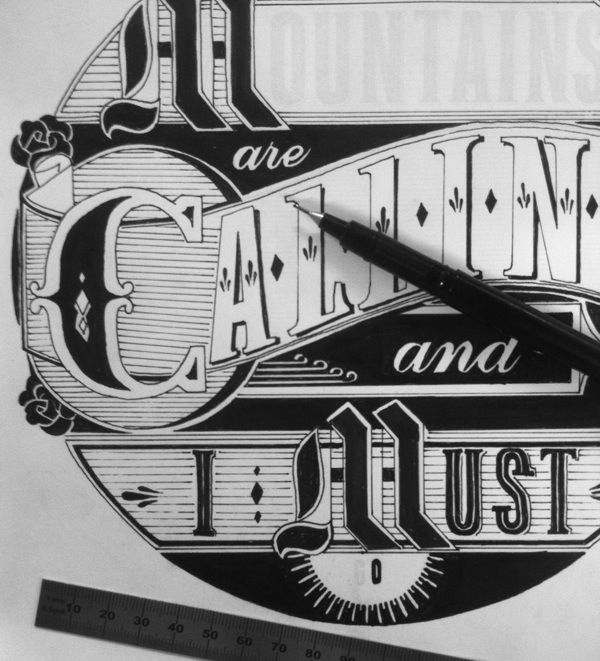
La habilidad de Ben Johnston como tipógrafo y su experiencia en el diseño industrial, junto al talento de Mark Simmons en la transformación en objetos 3D de imágenes impresas, han dado origen a este proyecto: la creación de esculturas de PLA (bioplástico) en las que las letras de Johnston adquieren profundidad y peso.
Tipografía 3D, Ben Johnston y Mark Simmons, 2014.
Ben Johnston, autodidacta canadiense de 26 años, se dedica a la ilustración de tipografías. Con su técnica de rotting negro sobre fondo blanco hace que las letras den forma a imágenes: dibujos, murales, sellos o diseños animados. Su experiencia en el diseño industrial ha permitido a este artista romper los límites de la bidimensionalidad y dar vida a sus tipografías, ahora convertidas en esculturas 3D. Ben Jonhston trabaja, desde su estudio en Toronto, como freelancer.
Tipografía 3D, Ben Johnston y Mark Simmons, 2014.
Diseño en 3D es un proyecto ideado por Ben Jonhston que, esta vez, decide colaborar con Mark Simmons en la realización de la obra. La motivación principal de ambos es la de crear una pieza única. El talento individual de cada autor, de Jonhston como ilustrador y de Simmons como proyectista, ha dado vida a estas esculturas que, como afirman, “ninguno de los dos habrían podido construir de manera independiente”.
Tipografía 3D, Ben Johnston y Mark Simmons, 2014.
Las esculturas en 3D combinan, así, dos disciplinas siamesas: el diseño gráfico y el diseño del producto. El proceso comienza con Jonhston que ilustra a mano y en línea negra una frase arrítmica, siempre asimétrica, decorada con relieves y sombras, para que después sea refinada ajustándola a un formato digital de vectores.
Tipografía 3D, Ben Johnston y Mark Simmons, 2014.
Para dar la forma 3D, los autores utilizan el programa CAD (Computer – aided designed) que asiste en la modificación, análisis y optimización de la imagen, perfeccionándola y mejorando su calidad. En el ordenador, el boceto es representado y animado hasta que finalmente, con una impresora 3D, Simmons hace del diseño, un objeto físico.
Tipografía 3D, Ben Johnston y Mark Simmons, 2014.
Cada escultura se limita, en su composición, a tres piezas, de manera que el volumen de material impreso es el mínimo. El material utilizado, denominado PLA, se ajusta, además, a un enfoque ecológico, ya que el bioplástico es un tipo de plástico derivado de productos vegetales, como el aceite de soja, el maíz o la fécula de patata que, a diferencia de los plásticos convencionales, no deriva del petróleo.
Tipografía 3D, Ben Johnston y Mark Simmons, 2014.
Las impresiones necesitaron paciencia y cincuenta horas de impresión cada una, y en el ajuste de las piezas, si seguimos prestando atención a los detalles técnicos, los autores utilizaron una máquina FFF (fused filament fabrication machine).
Tipografía 3D, Ben Johnston y Mark Simmons, 2014.
Diseño en 3D tiene la peculiaridad de ser una obra exclusiva, que escapa a la lógica del mercado en cuanto irrepetible, fruto del encuentro puntual entre dos artistas. De metafísico quizás tenga el singular encuentro entre las letras y la física: la tipografía, en principio destinada a grabarse en un plano liso, es, en este proyecto, materia que pesa entre las manos. No podríamos hablar, en cambio, de significado, pues las letras de Jonhston parecen, a primera vista, esquivar las interpretaciones para leerse como significantes, o lo que es lo mismo, como signos.
Tipografía 3D, Ben Johnston y Mark Simmons, 2014.